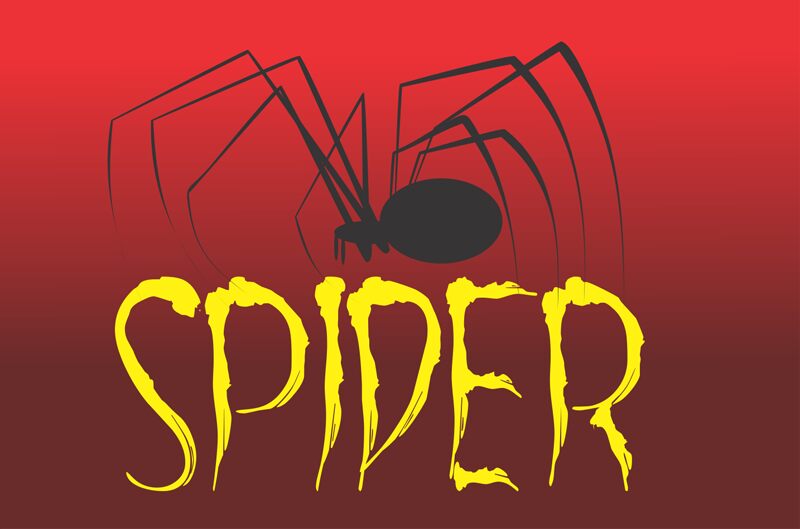
Aracnoide to darmowy, zniekształcony krój typu display o horrorowym charakterze, z chudymi, wyciętymi ręcznie literami. Poszarpane krawędzie, nagłe kolce i rozlane pociągnięcia sprawiają, że formy przypominają rozmazany tusz lub poszarpane sylwetki.
Może nadać okładce metalowego albumu groźny wyraz, a dzięki swojej niestabilnej, przypominającej pazury konstrukcji sprawdzi się również na plakatach na Halloween i w grafikach gier z dreszczykiem. W wydawnictwach najlepiej pasuje do nadprzyrodzonych nagłówków okładkowych, w których nieregularne kreski mogą nawiązywać do podrapanych lub mrocznych ilustracji.
Ten krój pisma był częścią rodziny spider.